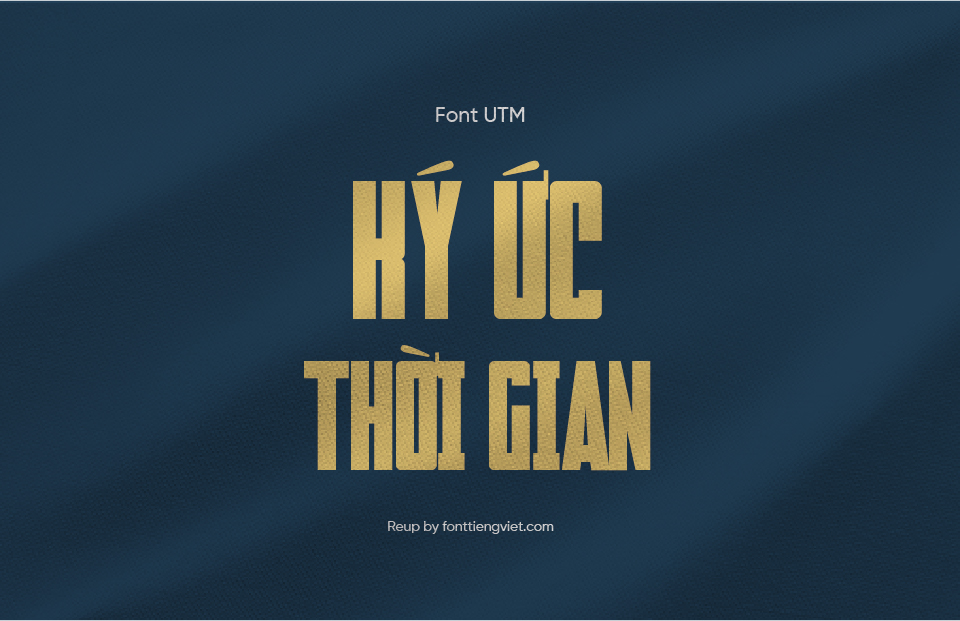
Font Việt hóa UTM Faltura
Giới thiệu về Font Việt hóa UTM Faltura
Trong thế giới thiết kế đồ họa tại Việt Nam, việc tìm kiếm một Font Miễn Phí có hỗ trợ tiếng Việt đầy đủ luôn là ưu tiên hàng đầu của các bạn học sinh và giáo viên. Font Việt hóa UTM Faltura nổi lên như một lựa chọn hoàn hảo nhờ phong cách thiết kế hiện đại, mạnh mẽ nhưng không kém phần thanh thoát. Đây là bộ phông chữ thuộc dòng UTM nổi tiếng, được tinh chỉnh kỹ lưỡng để phù hợp với bảng mã Unicode, giúp người dùng dễ dàng gõ tiếng Việt có dấu mà không lo lỗi hiển thị hay bị mất ký tự đặc biệt khi soạn thảo văn bản hoặc làm slide thuyết trình.
Những đặc điểm nổi bật của bộ Font Việt hóa UTM Faltura
Kiểu dáng hiện đại và tính ứng dụng cao
Font Việt hóa UTM Faltura sở hữu những đường nét dứt khoát, hình khối rõ ràng, mang lại cảm giác chuyên nghiệp cho mọi khung hình. Với độ dày nét chữ vừa phải, phông chữ này cực kỳ thích hợp để làm tiêu đề bài giảng, thiết kế bìa sách giáo khoa hoặc tạo các biểu mẫu thông báo trong nhà trường. Sự cân đối giữa các chữ cái giúp người xem dễ dàng tiếp nhận thông tin ngay cả khi quan sát từ xa.
Khả năng tương thích trên nhiều nền tảng
Kết luận và cách sử dụng font chữ hiệu quả